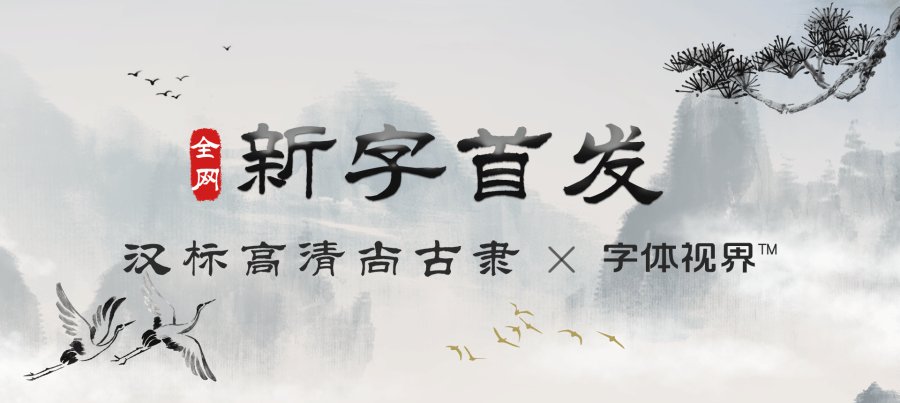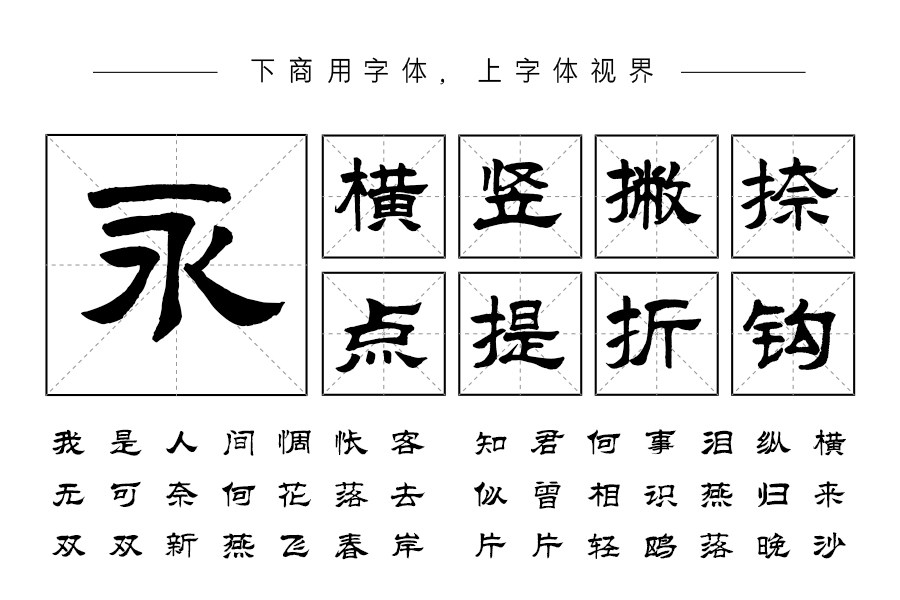
一款带有书法味道的纯毛笔手写字体—汉标高清尚古隶
无论是上班族还是学生们,放假通知是大家最想看到的通知,翻看日历,年后第一个小长假——劳动节已经悄悄地在向我们招手了。各路放假通知、品宣海报都已齐刷刷上线,在这个春夏交接的时段,是一个消费较为活跃的时期。因此我们一定要提前做好促销宣传。做宣传当然少不了精美字体的身影啦。今天给大家带来一款全网首发新字——汉标高清尚古隶。
汉标高清尚古隶
汉标高清尚古隶:一款带有书法味道的纯毛笔手写字体,参考古代隶书精华融入现代美感,字型偏扁方,笔画中也减少了过多的处理和笔势,厚重、饱满。因为是纯手写的原因,它独特的气质更与其他字体不同,看似统一,其实各有各的味道,每个字都可以独具风情。